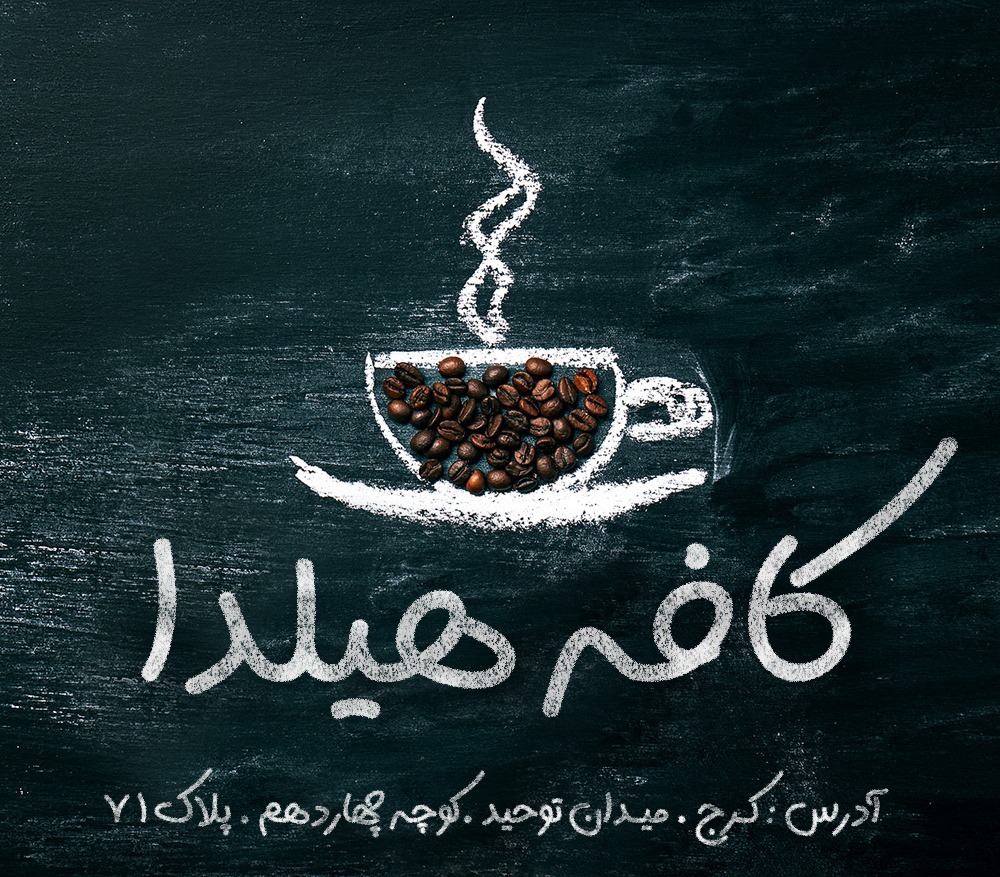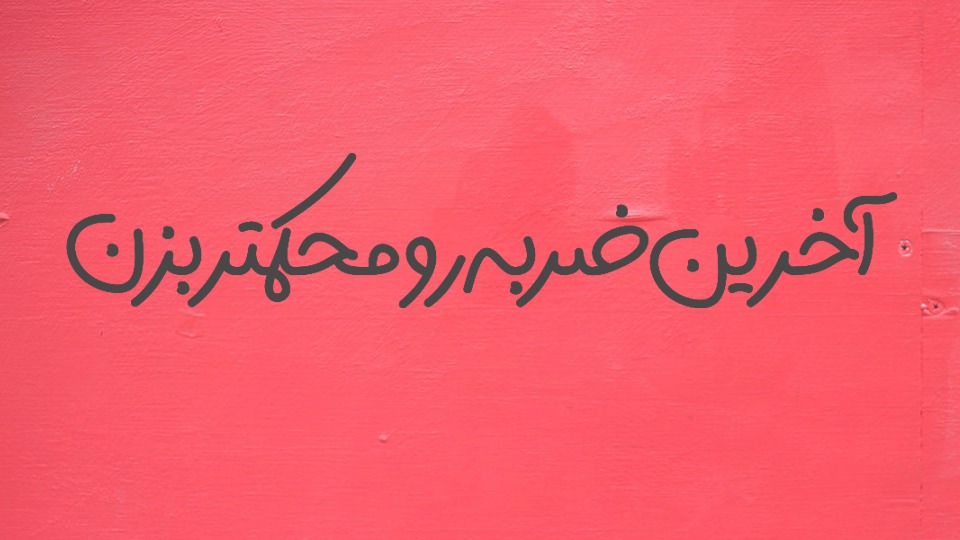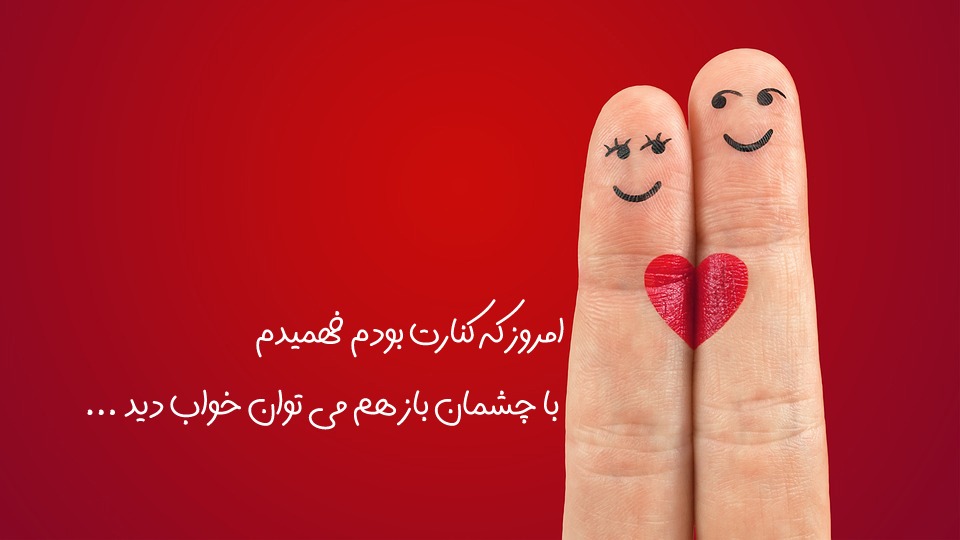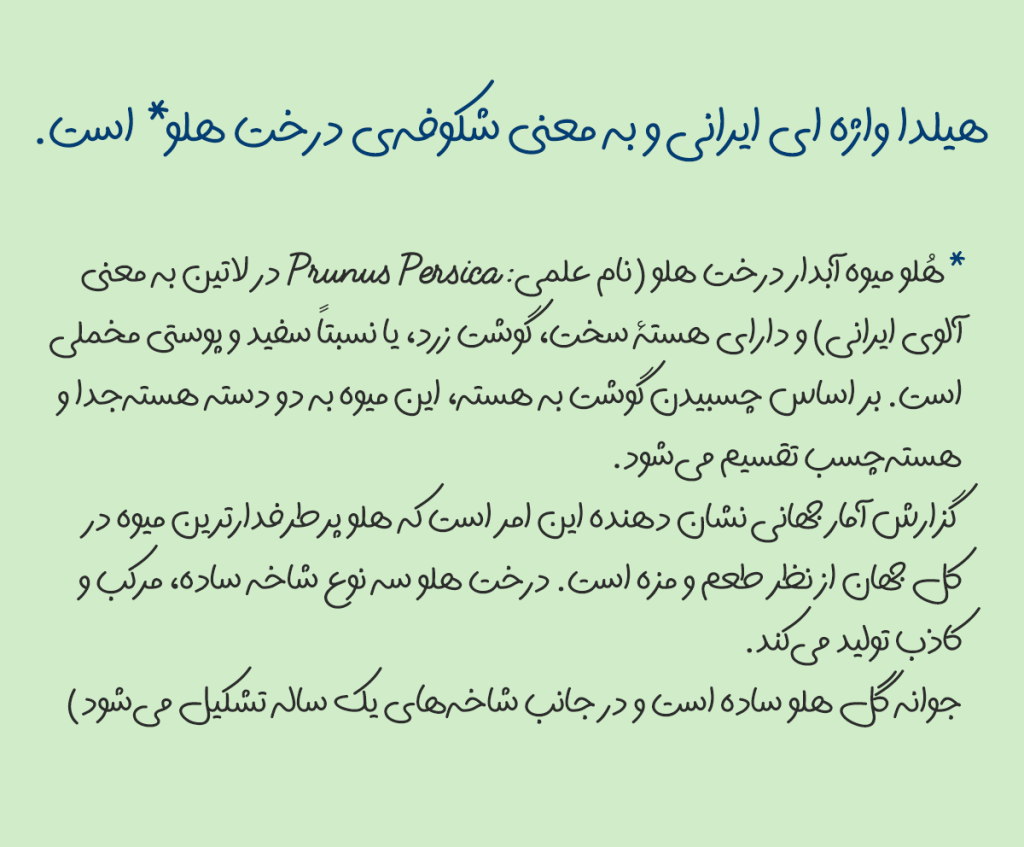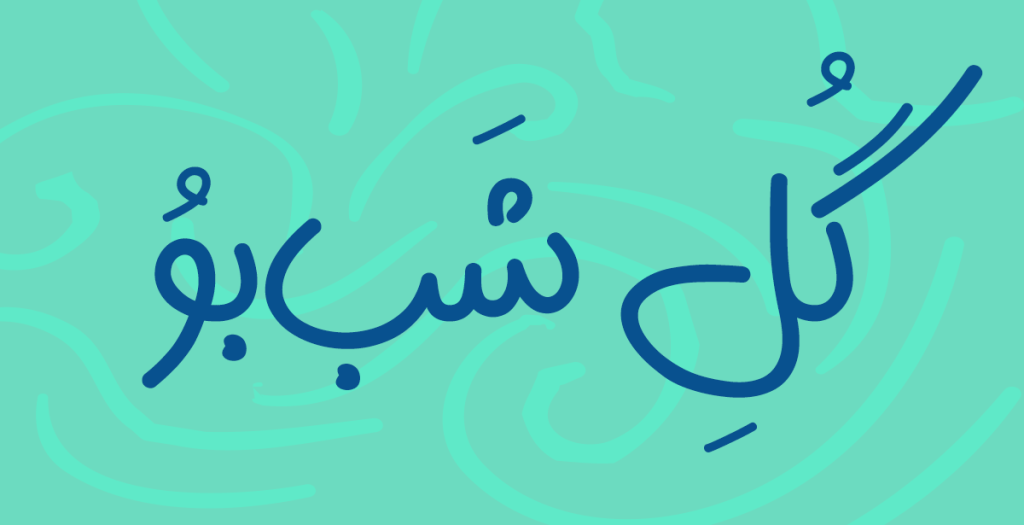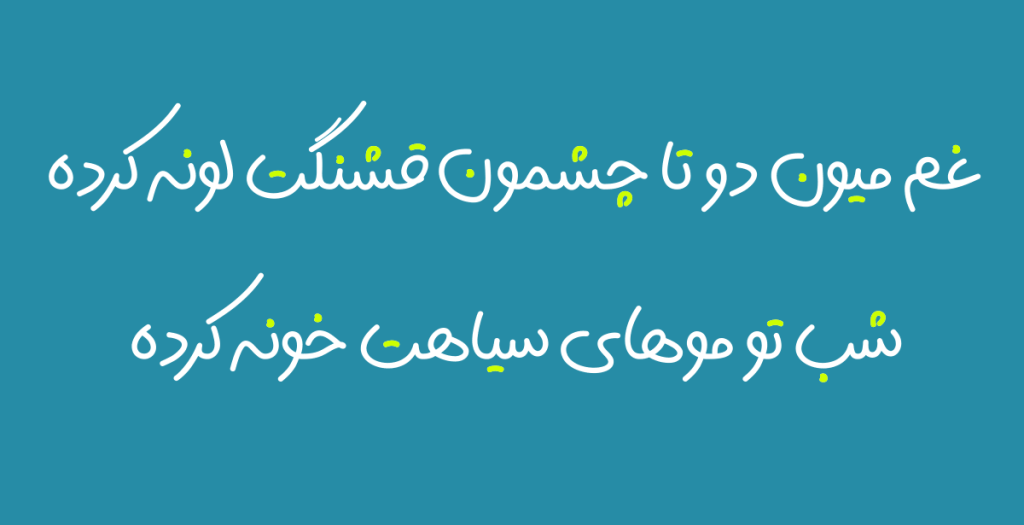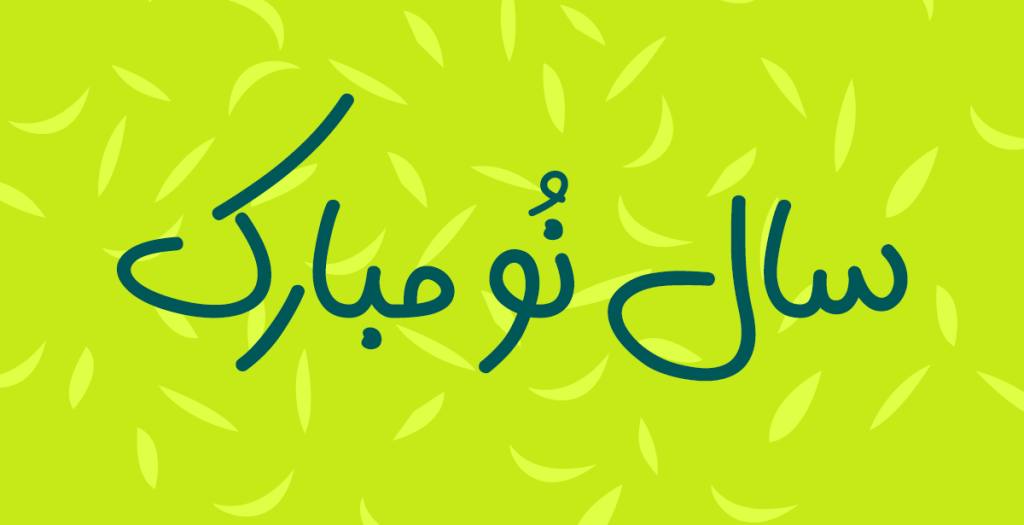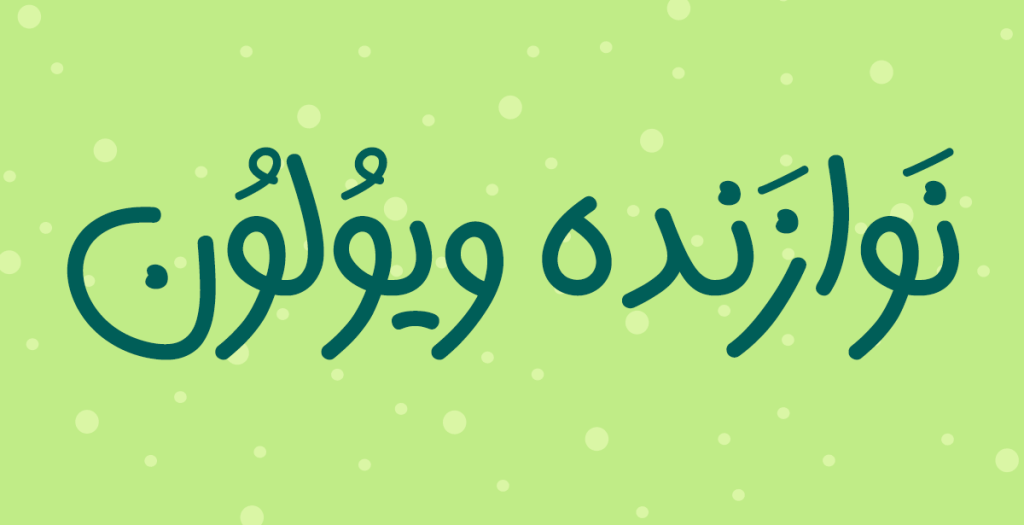
فونت هیلدا
فونت هیلدا ساخته شده توسط محمد عمویی از خانواده تایپ فیس های دست نویس می باشد. یکی از ویژگی های خانواده دست نویس به سبب نزدیکی به دست خط انسان و گرفتن ارتباط قوی با این نوع از فرم های طراحی دارای فضای ارتباط گیری گرم و صمیمی می باشند و مناسب برای تایپوگرافی در این نوع از فضاهای طراحی هستند.
با اندکی دقت در این قلم می توان دریافت که بسیاربه دست خط انسان نزدیک است گویی آدمی آنر ار نوشته است. این قلم از دسته تایپ فیس های منولاین و بدون کنتراست است. هیلدا شخصیتی گرم و گیرا دارد که دارای ویژگی نمایشی و جذب کننده نگاه ها به خود می باشد.
هیلدا قلمی دست نویس و گرم و صمیمی
فاکتور تعادل و میانه روی در هیلدا جزء اصول اصلی آن است. نه آنقدر رها و آزاد نه آنقدر کنترل شده که تبدیل به قلمی ساده و روان تبدیل گردد. محمد عمویی پیش از طرح هیلدا فونت مانلی را طراحی و ابداع نموده. اگر به تایپ فیس های دست نویس علاقه مند هستید و نیاز به این نوع از کاربرد در طرح های خود دارید. می توانید از طریق لینک سطر بالا از مانلی نیز دیدن کنید. چرا که واقعا زیبا و جذاب است.
نسخه اول از این قلم دارای ترکیبات محدودی و فاقد ترکیبات جایگزین می باشد، اما در نسخههای بعدی طبیعتا تعداد ترکیبات افزایش خواهد یافت و ترکیبات جایگزین نیز اضافه خواهد شد.این قلم مناسب متون محاوره ای ، تبلیغاتی و .. می باشد.